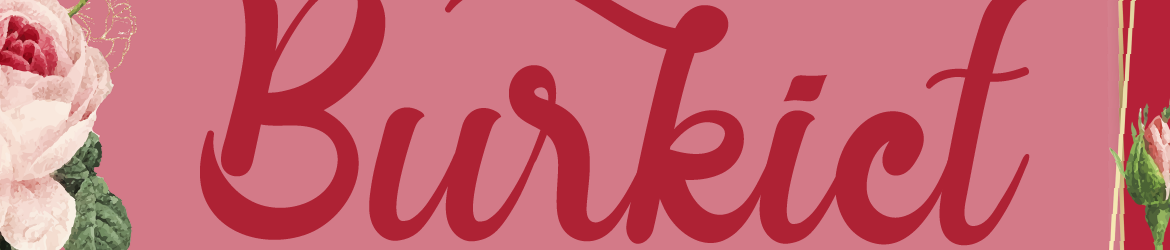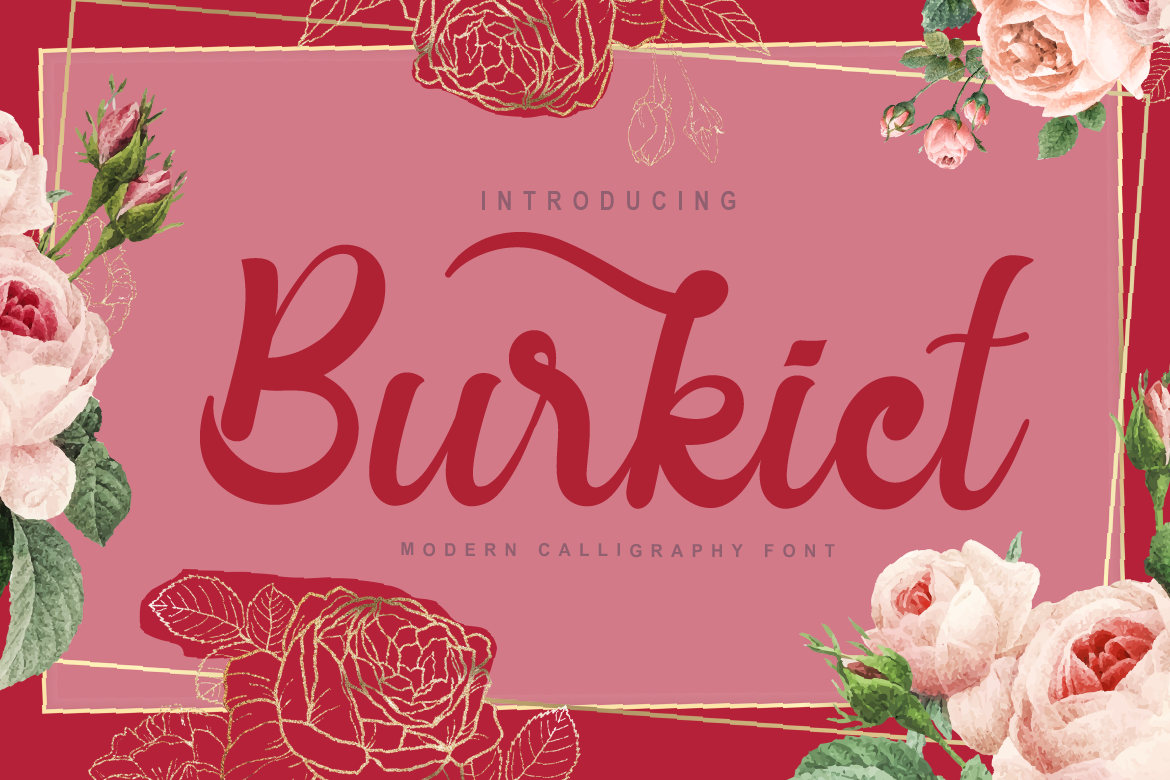
Burkict Font – Fonte Grátis
Burkict Font
Esta é uma fonte de escrita chamada Burkict Font, criada pelo designer Makaryo. Ela transmite sofisticação e elegância através de sua elegante tipografia que se destaca como a escolha perfeita para qualquer projeto. As alternativas estilizadas e ligaturas são particularmente úteis para quem deseja adicionar um toque único, reforçando ainda mais o charme desta fonte. Inspirada em scripts clássicos modernos, Burkict é uma opção ideal tanto para criações de escrita formal quanto para design gráfico criativo. Combinar este recurso visual com qualquer projeto, a fonte atesta que estilo e funcionalidade se combinarão perfeitamente, tornando-a um investimento valioso para designers em busca de algo diferenciado e sofisticado.